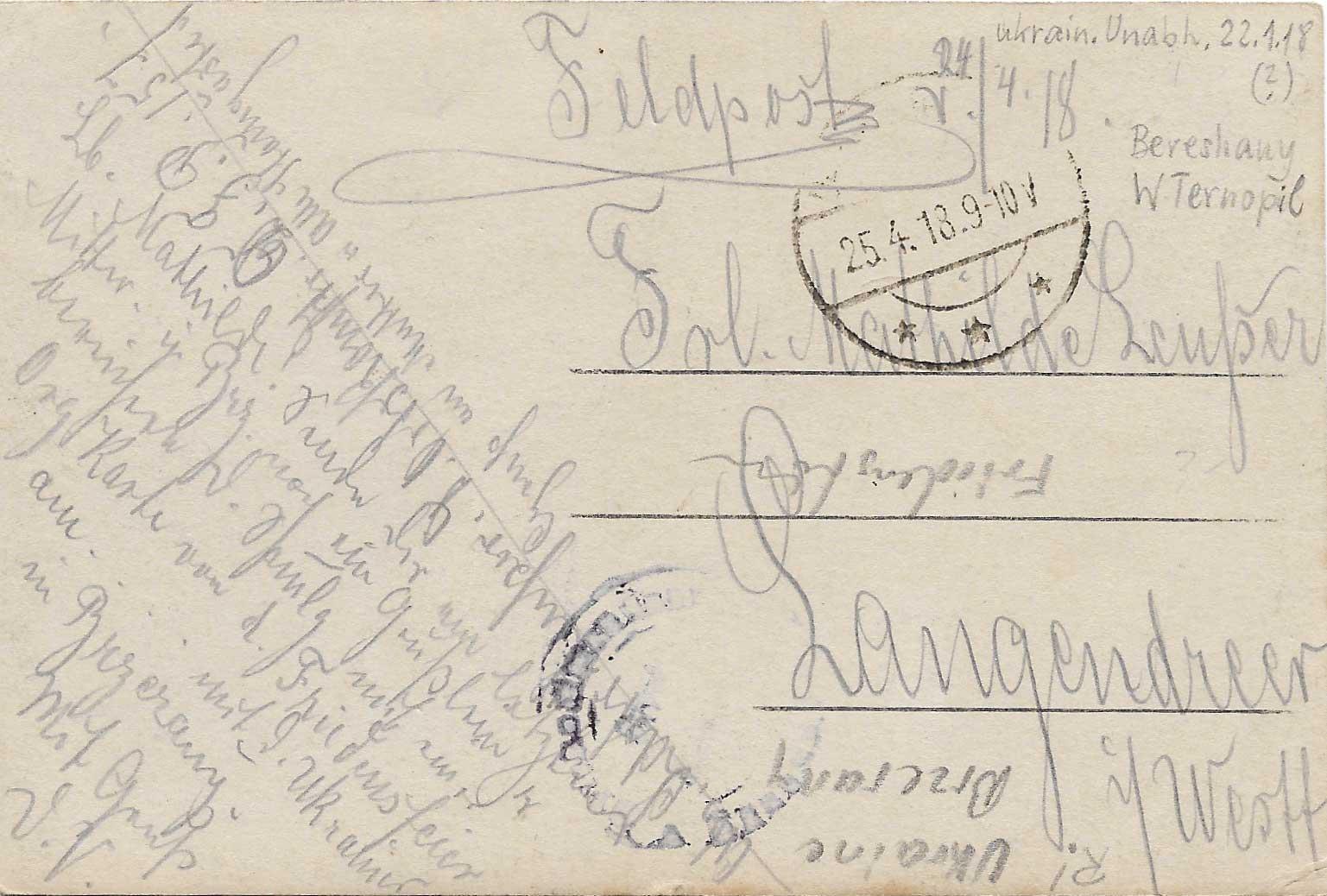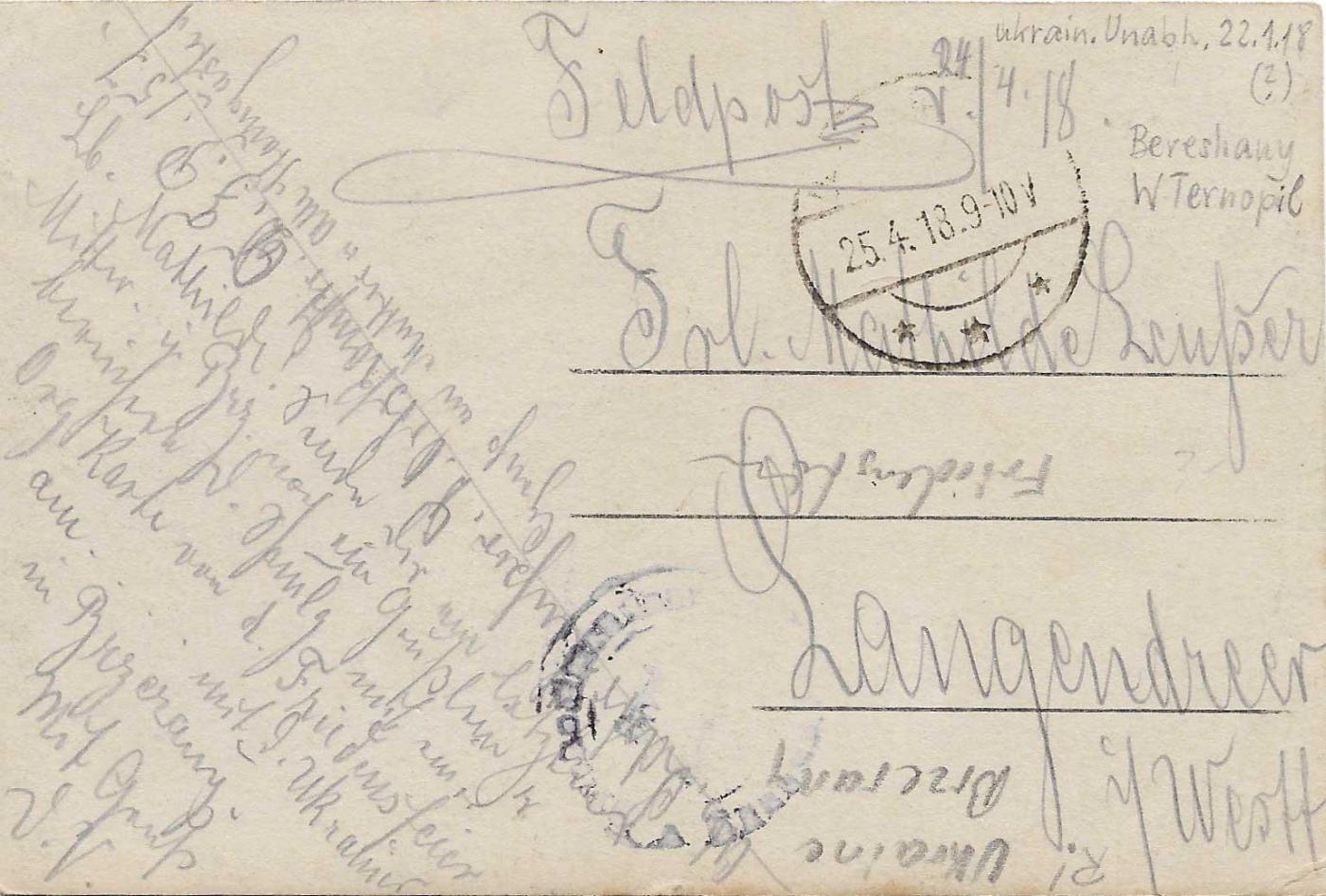
Unterstützung bei Entschlüsselung einer alten Handschrift
kann mir jemand helfen bei Entschlüsselung der Handschrift auf den zwei angehängten Postkarten?
Ich lese: Anblick der Stadt Sevastopol --- viel Fotopapier von hinten ---  2. Juli 1942
Aha, jetzt sehe ich die Karte - und muss sie mehrfach drehen...
in der abgebildeten Richtung:
Ukrain. Unabh. 22.1.18 (?)
Feldpost v. 04/4.18.  Bereshany W Ternopil
Frl. (Fräulein) Mathilde Leußer
(kopfstehender Text)
Langendreer
is (?) Westf
180° gedreht:
R!
Brzerany
Friedensf... (?)
Schräg:
(durch Stempel unlesbar) D. Ortskom??tr. D. F. P. 15 J(?)
Gruß an Mutter u. alle Stammgäste (mit m mit Überstrich zur Verdoppelung)
wieder 180° zurück gedreht:
Lb. Mathilde. Sende dir eine letz???? (unlesbar durch Stempel)
(an der Zeile rätsel ich noch herum...)
Originalkarte von d. Friedensfeier
am . . . . mit d. Ukraine
in Brzerany
mit Gruß
d.V.
Bitte nicht. Meist bringt das Hineinzoomen notwendige Details ans Licht.
Liebe Mathilde! Sende dir am letzten
Mittwoch in Brzezany noch ein Grußlein [–] er
bereichere die Sammlung mit einer
Original-Karte von der Friedensfeier
am ... mit der Ukraine
in Brzezany.
Mit Gruß
der Vati
Ein paar Lesarten sind nicht ganz sicher: beim "Mittwoch" bin ich z.B. unentschieden, aber der 24.4.1918 war tatsächlich ein Mittwoch; und das "V." am Ende könnte natürlich auch "Vater" heißen. Die Abkürzungen sind aufgelöst (z.B. "Samlg." mit Verdopplungsstrich über'm "m"). Gibt es denn die Karte von der Friedensfeier, die hier erwähnt ist?
Ach ja, "Sewastopol" auf der Rückseite der Fotografie mit "w" statt "v".